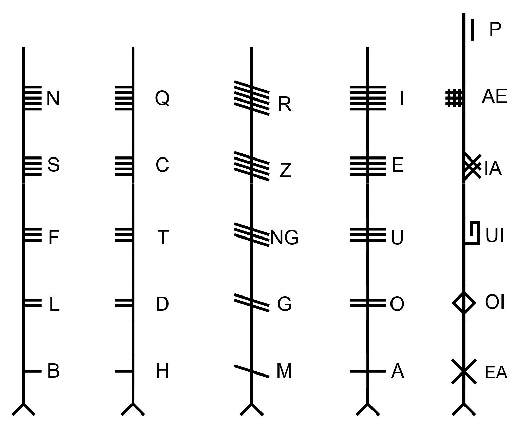
Nordisch bis 900
Die Ogham-Schrift ist für Irland und Schottland belegt. Sie diente vor allem dazu, auf Grenzsteinen einen Besitzanspruch geltend zu machen, und wurde bis etwa 800 n. Chr. genutzt.
In Büchern erscheint die Ogham-Schrift nur selten. Sie ist vor allem in Stein geritzt: senkrechte Striche links und rechts einer Kante stehen für die einzelnen Laute. So entstanden frühe Besitz- und Grabmarkierungen in den keltischsprachigen Gebieten der Britischen Inseln.
Ein Inisfallen-Ogham-Text bringt den Geist seiner Zeit auf den Punkt: „Geld ist geehrt, ohne Geld ist niemand geliebt.“
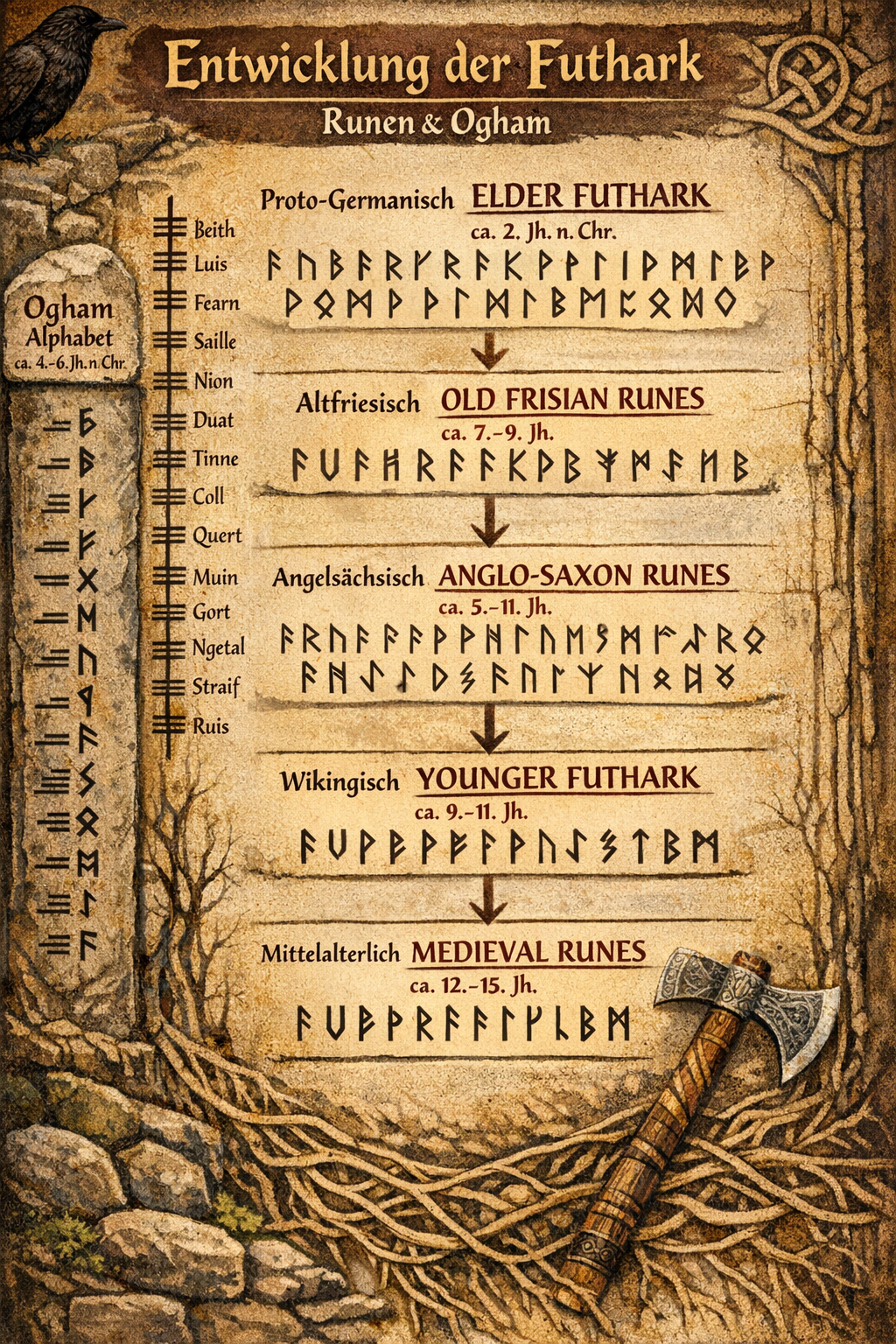
Norden vor dem Pergament
Steine, Stäbe und erste Bücher
Germanen mit frühen Schriftzeichen
Vor 800 n. Chr.
Schrift bei den Germanen
Im Norden Europas ist Schrift lange Sache der Sippe, nicht des Buches. Runen werden in Holz geritzt, in Stein geschlagen oder in Knochen gekratzt — sie markieren Besitz, beschwören Götter und halten Namen über den Tod hinaus fest.
Ogham-Zeichen an einer Steinkante
Irland & Schottland
Die Ogham-Zeichen
Links und rechts einer scharfen Kante stehen schmale Striche — jedes Bündel ein Laut. Die Ogham-Schrift ist auf die Geometrie des Steins zugeschnitten und wirkt wie eine in Granit gefräste Tabelle.
Ogham-Schrift in einem Buch
Spätere Überlieferung
Ogham im Buch
Erst im Mittelalter findet die Ogham-Schrift den Weg aufs Pergament. Mönche und Gelehrte zeichnen die Zeichen ab, ordnen sie in Tafeln und sichern so eine Schrift, die zuvor ganz an ihre Steine gebunden war.